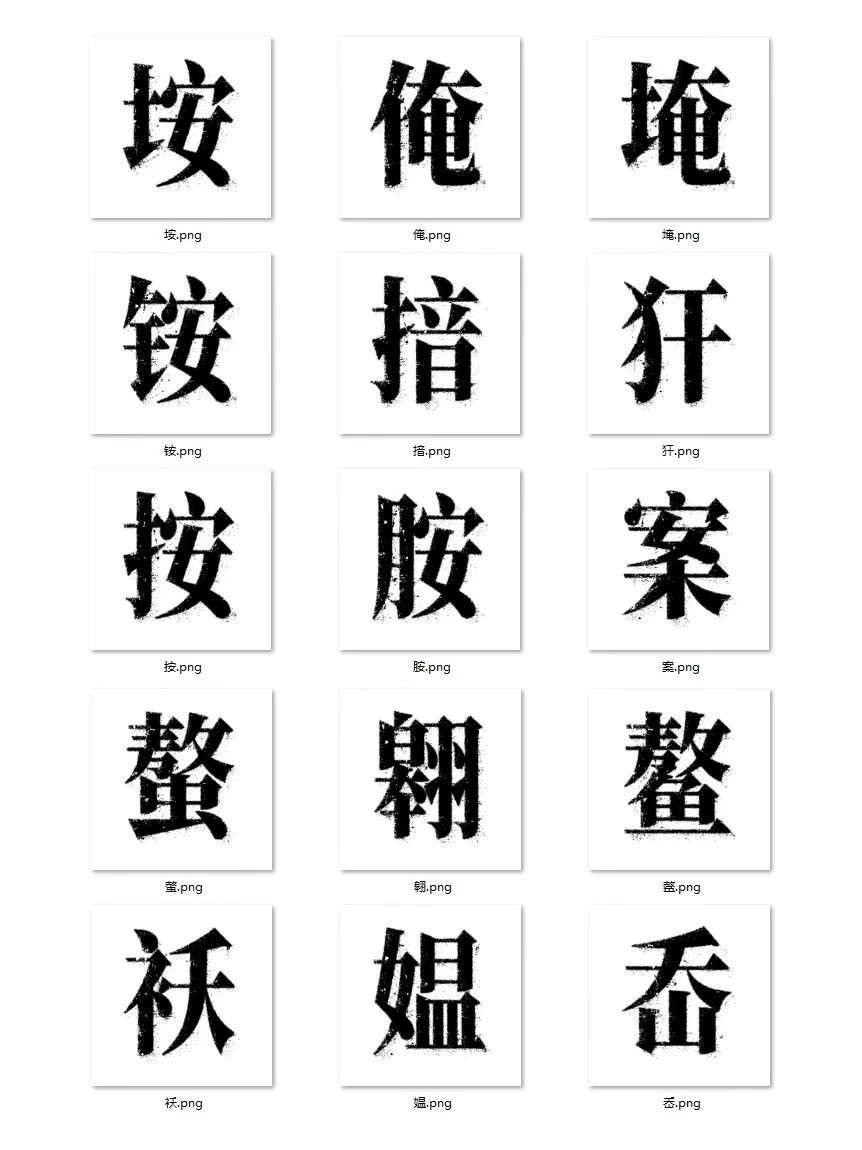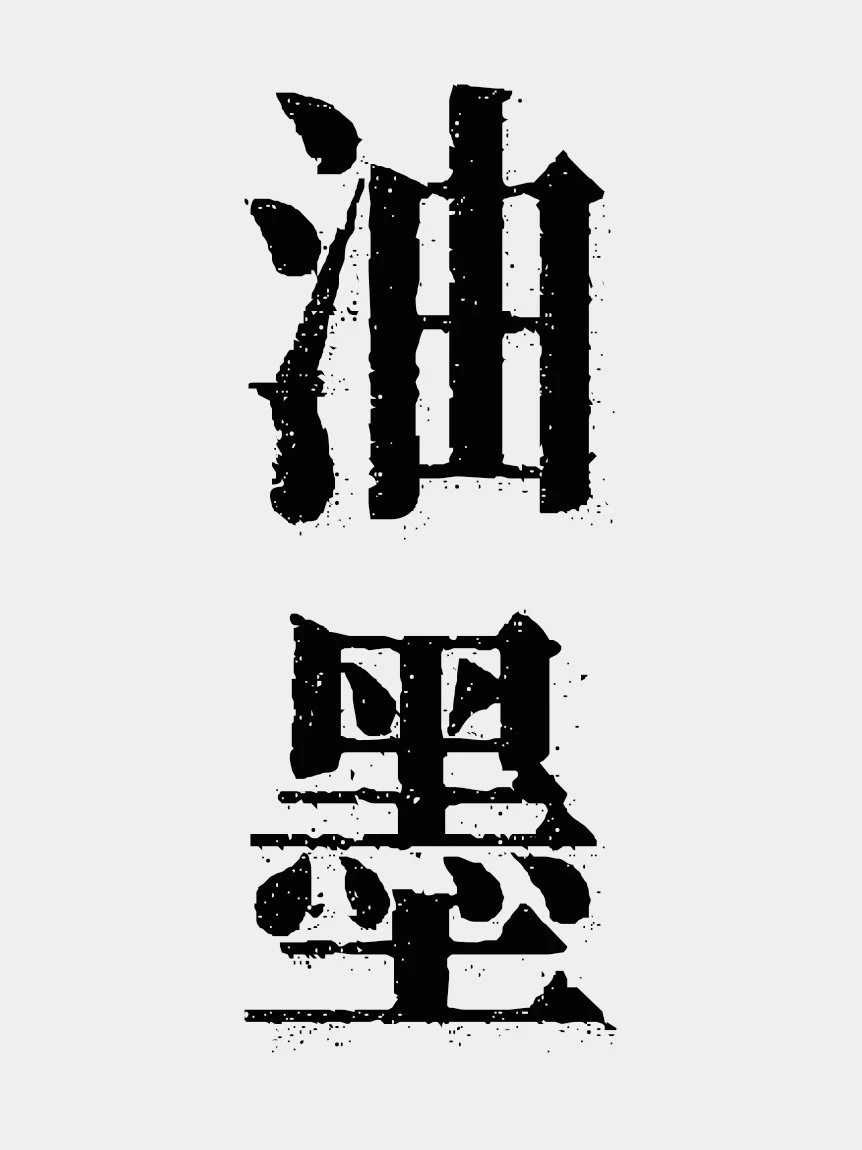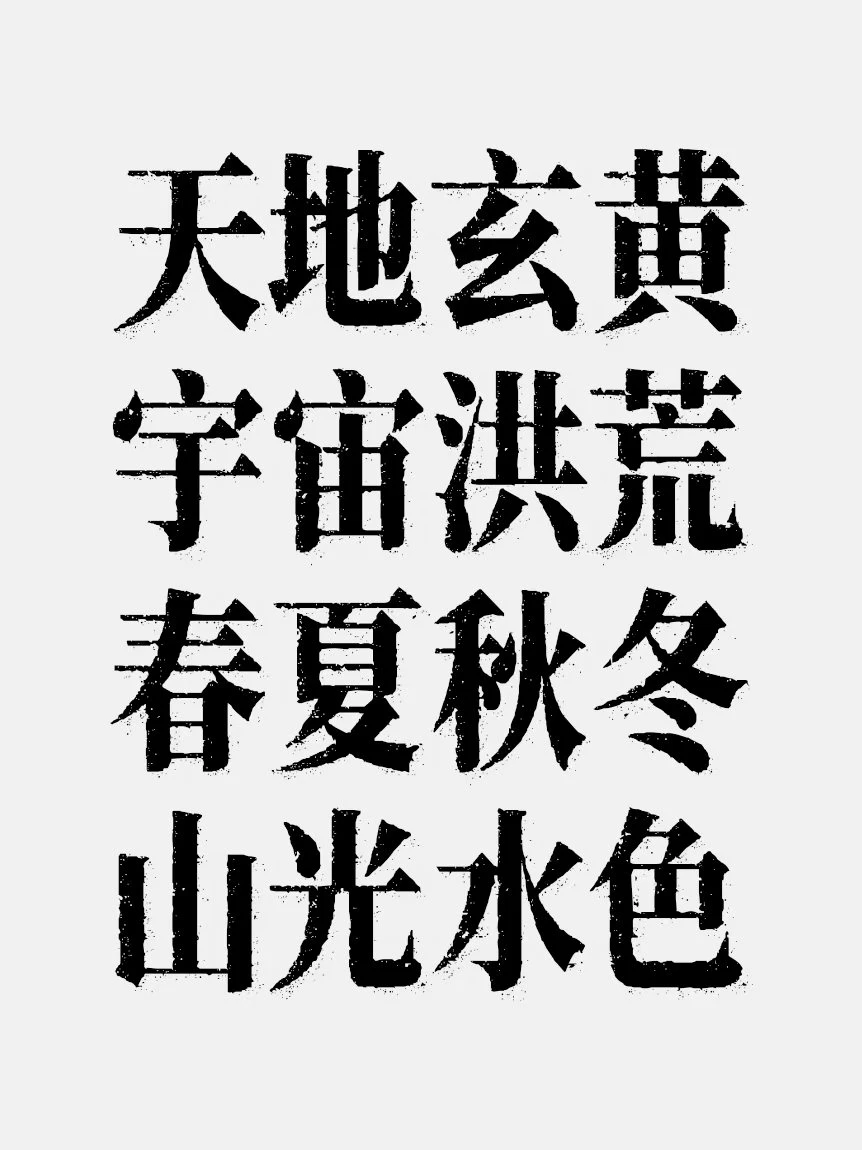
南西油墨宋是以思源宋体为基础进行再创作,遵循 SIL OFL 开源协议发布的一款免费商用复古风格宋体字。这款字体在视觉上还原了老式活字印刷的典型质感,其表面模拟出细微的油墨颗粒与斑驳不齐的毛边效果,让每一笔画都带有手工时代的温度与痕迹。在设计上,南西油墨宋特别强调笔画的厚重感与结构的力量感,衬线部分清晰明确且富有装饰性,这种鲜明的特征使其非常适合用于需要突出视觉冲击力的大字号标题场景。无论是带有复古国潮气息的海报、充满工业风格的视觉设计,还是书籍封面、商品包装乃至短视频的标题封面,南西油墨宋都能直接融入并提升整体氛围,为作品增添一份扎实、怀旧且富有表现力的排版基础。